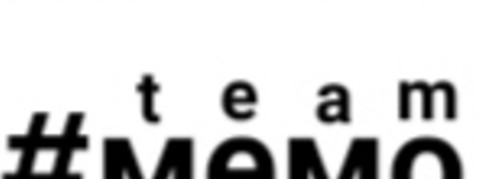
Welche Schriftart ist das - kurz vor dem Verzweifeln!
weiß jemand, wie man sowas hinbekommt?
Also dieses "team" über einem normalen Text.
Welche Schriftart ist das, ich bin so langsam vorm Verzweifeln...
Ich weiß, daß es über einen Schriftgenerator gemacht wurde, leider nicht über welchen.
Ich brauche das in der Form, in der ich das per copy und paste einfügen kann. (als Benutzernamen in einer APP)
sieht für mich ähnlich zu Arial FETT mit zweit Leerzeichen zwischen den Buchstaben aus.
t e a m
Oder jemand hat mal Geld in die Hand genommen. ;)
Arial ist es fuer mich nicht, das "t" ist oben schraeg bei Arial.
Ich bin fuer "Neuzeit S LT Std Book Heavy", auch wenn das "a" nicht ganz passt.
Da die Buchstaben nicht auf einer gemeinsamen Grundlinie sitzen (beim "e" ist es besonders deutlich), ist das Original vermutlich tatsächlich ein Bild, oder der Font Renderer ist richtig schlecht.
Es geht ja darum, daß das team hochgestellt ist, man aber beides über eine Schriftart schreiben kann.
Nein, es ist kein Bild da sich in der App nur Schriften per copy and paste einfügen lassen können
Nochmal, es geht um eine Schriftart die aus diesen beiden Schriftarten besteht....das untere + das obere "team"
Die Schriftart ist Google Roboto. Dann wurde die Schriftart wohl in einen Fonteditor geladen und die kleinen Buchstaben über den größeren platziert, wobei der Offset für jeden kleinen Buchstaben unterschiedlich ausgefallen ist, so dass die Grundlinie nun flattert.